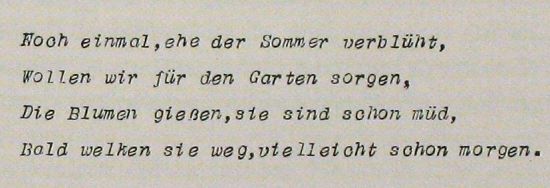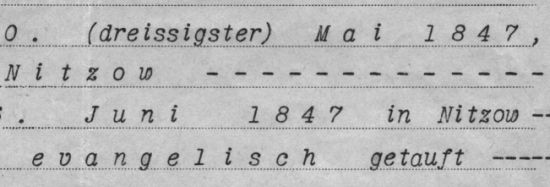
Mechanische Schreibmaschine kursiv
Mechanische Schreibmaschinen mit kursiver Schrift gab es, im Verhältnis zu denen mit »normaler« Schrift, nur selten. Ich besitze einige ältere Schriftstücke, die mit einer solchen Maschine geschrieben wurden.
Meine Frage: Gibt es eine entsprechende Schrift auch in digitalisierter Form (TTF)? Zur Veranschaulichung füge ich eine Schriftprobe bei.
Hier noch eine andere Schriftprobe (aus: Hermann Hesse »Im Garten«)
Lacrima - Light Italic » Lacrima - Regular Italic » Lacrima - Bold Italic
Designer: Alexander Meyer
Lacrima is inspired by an old typewriter font called ‘Light Italic’. Meyer has digitalized this font and reinterpreted it giving it the new name, Lacrima (Italian for teardrop) after the little teardrops at the ends of some of the lowercase letters. Handy for creating corporate trademarks.